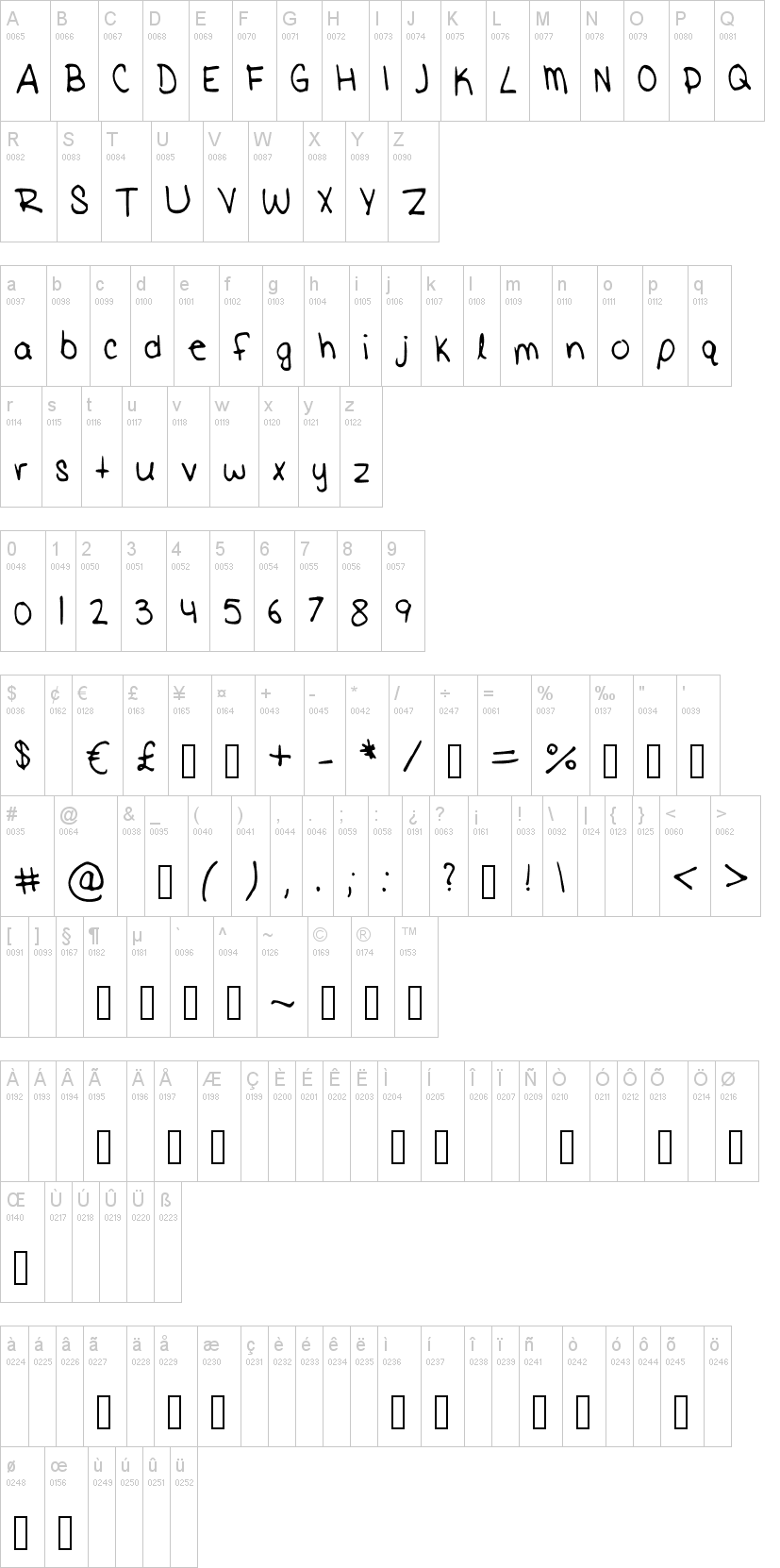
Elise
Elise 是一款免费的手写风格字体,由英国的设计师 Denise Bayers 制作。它的外观类似于手写信件,带有自然的笔画和流畅的线条,非常适合用于书信、卡片、海报等个人和商业项目中。 Elise 字体包括了大写和小写字母、数字、标点符号和一些特殊字符。它还包括了多种字体格式,包括 TrueType (.ttf)、OpenType (.otf) 和 Web 字体 (.woff)。这使得它可以在许多不同的应用程序和平台上使用,包括 Microsoft Word、Adobe Photoshop、和网页设计。 总的来说,Elise 字体是一种非常优美和实用的字体,适合于许多不同的设计和排版项目。
Elise是一款非常不错的手写艺术字体,具有很好的视觉感,适合于文化类的宣传设计、商业类品牌的广告和产品包装设计以及个性化文字排版等较多场景。
Elise字符映射图